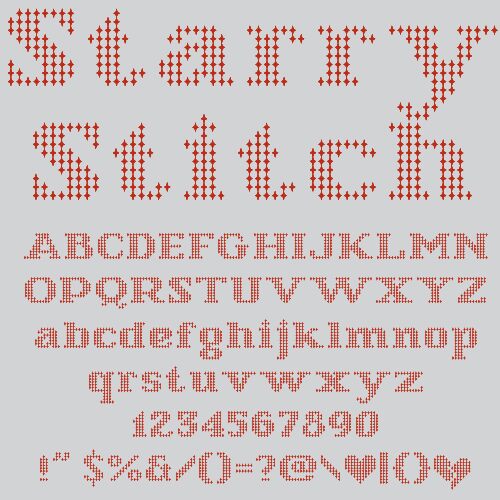
Starry Stitch di Nils von Blanc è un font bitmap gratuito di tipo display costruito su file ordinate di minuscole stelle a quattro punte. Le lettere seguono un ritmo a griglia a bassa risoluzione, mentre i loro tratti simili a un ricamo ammorbidiscono la struttura digitale con un tocco celestiale e fatto a mano.
Il motivo ripetuto delle stelle crea una texture scintillante nelle composizioni, conferendo ai poster di eventi e alle grafiche musicali un'atmosfera luminosa, come di costellazioni ricamate. Usa questo font gratuito per schermate di titoli di giochi, packaging artigianale e grafiche per i social media, quando vuoi che le lettere facciano da ponte tra la cultura pixel e il ricamo decorativo, senza bisogno di ulteriori ornamenti.
Starry Stitch è stato originariamente clonato da FontStruction Melt x tDR.